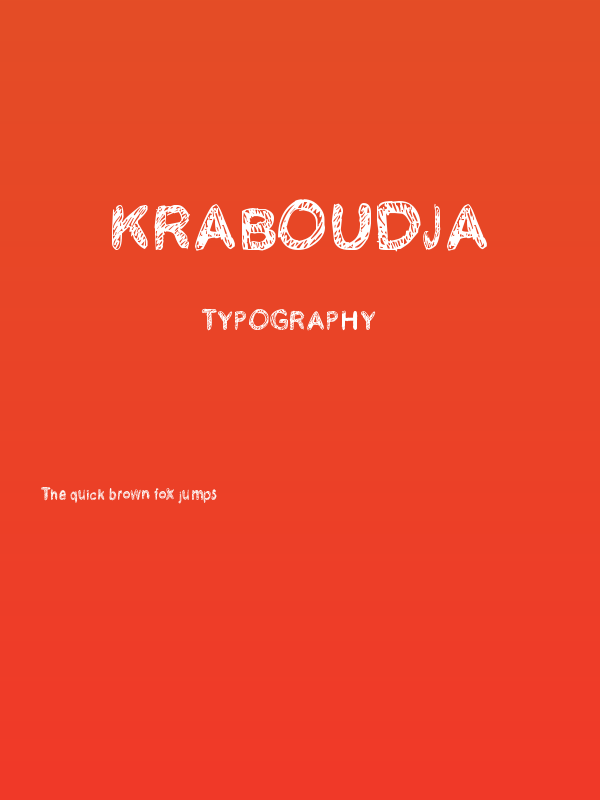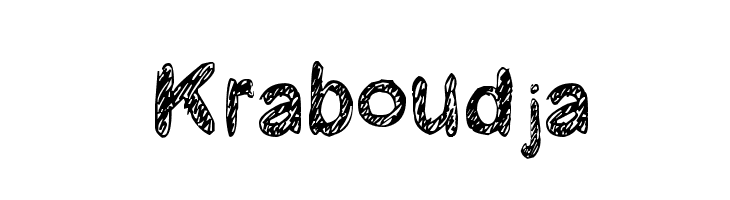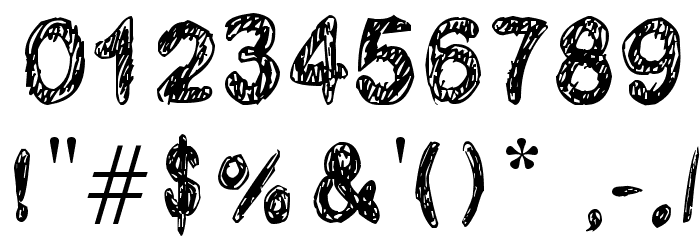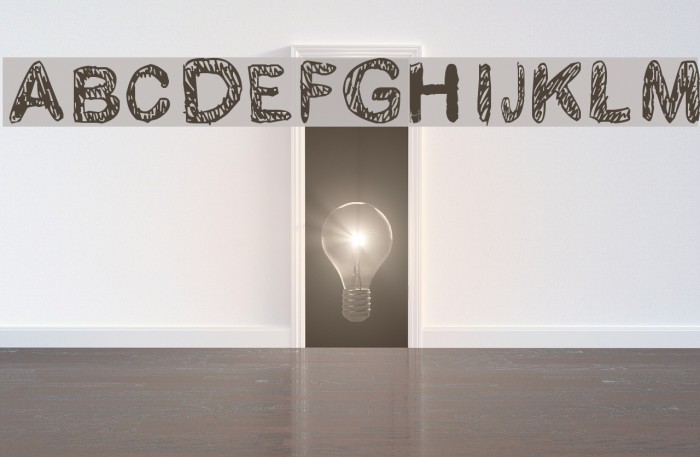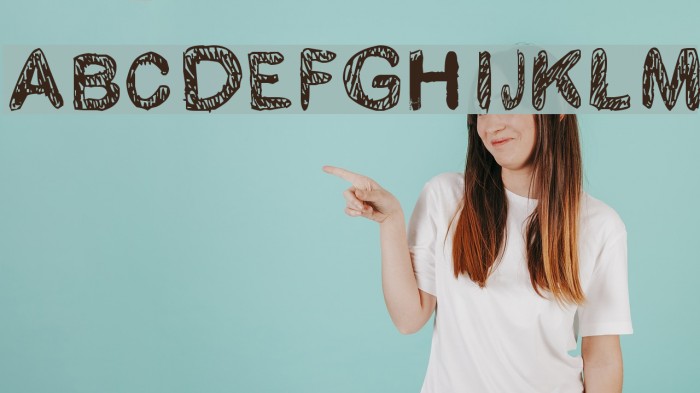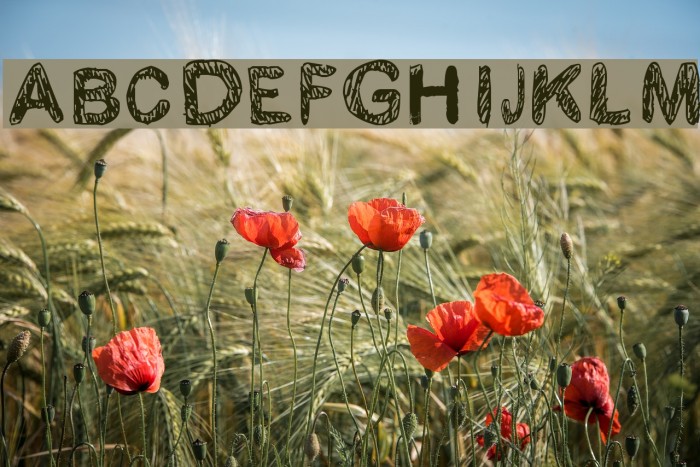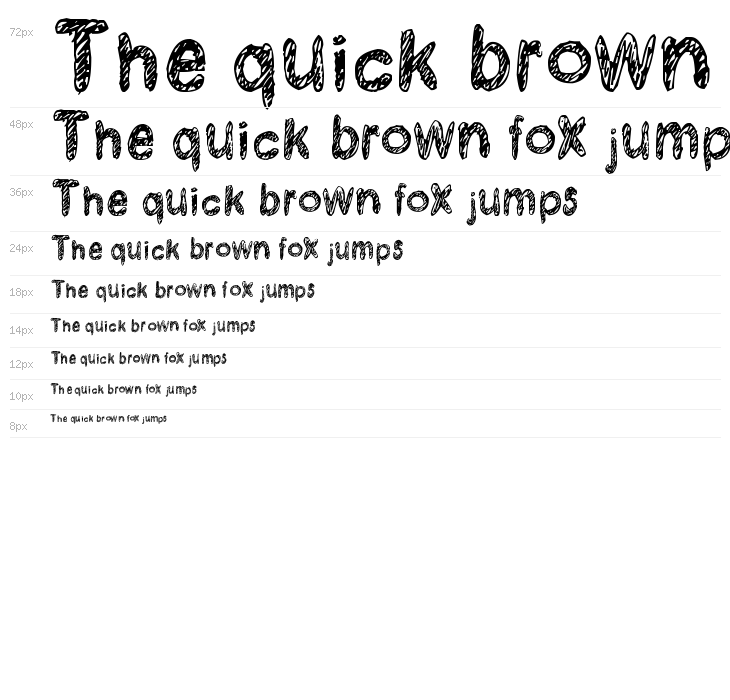
Kraboudja Font
| 全体的なスタイル | Playful, Artistic |
| おすすめプロジェクト | Ideal for children's books, creative posters, playful branding, and artistic invitations. |